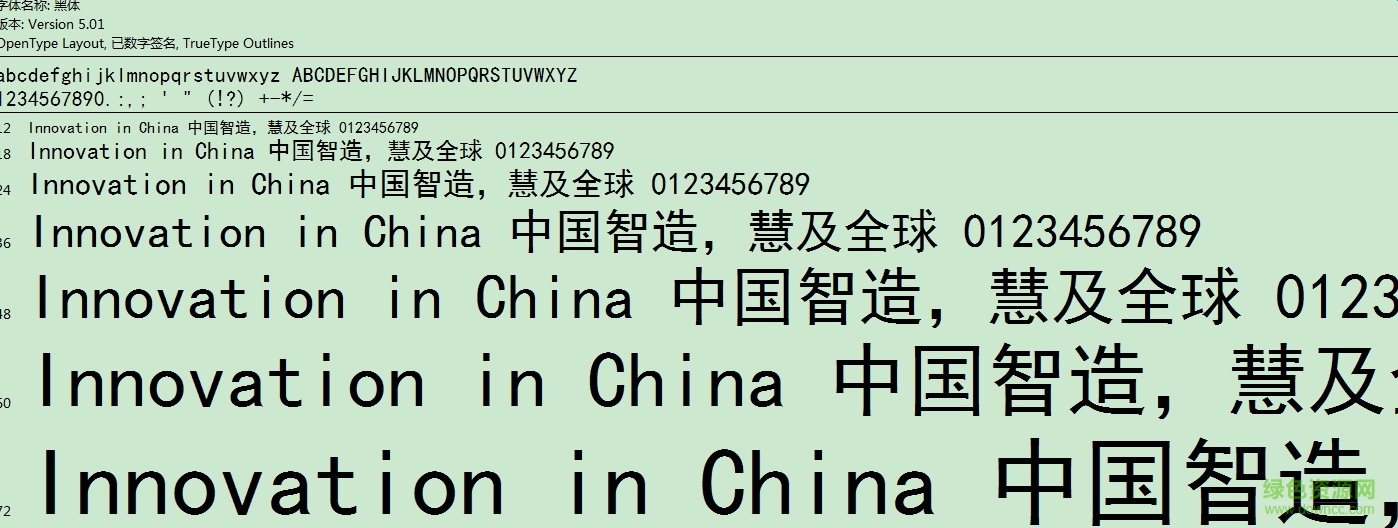
黑體常規(guī)西方字體是一款中規(guī)中矩的黑體字體,常常用在網(wǎng)頁(yè)顯示上,屬于無(wú)襯線字體類(lèi),樸素干凈均勻,分辨率高,可適合的范圍廣泛,需要的小伙伴快來(lái)綠色資源網(wǎng)下載吧!
可細(xì)分為:粗黑、超粗黑(特黑)、大黑、細(xì)黑、美黑、宋黑、水黑、藝黑、氈筆黑、平黑等類(lèi)型。
美術(shù)黑體幾何的筆型、機(jī)械的直線、透視的空間和模擬光照而形成的立體投影,這些細(xì)節(jié)處處流露出強(qiáng)烈的現(xiàn)代趣味與西方文明的痕跡。